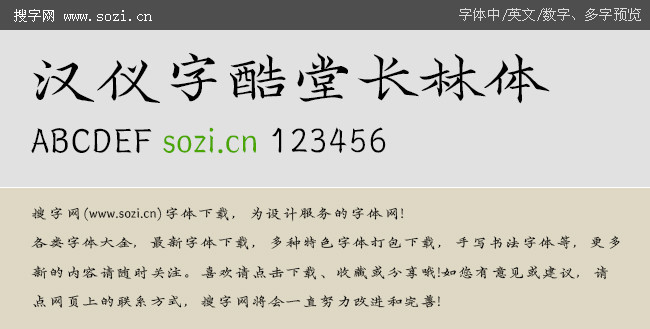
漢儀字酷堂長(zhǎng)林體
搜字網(wǎng)給大家提供一款漢儀字酷堂長(zhǎng)林體中文字體下載,漢儀字酷堂長(zhǎng)林體來源于清代名臣陳廷敬代表作品《午亭文編》,由林佶手書上版,結(jié)構(gòu)扁長(zhǎng),豎排效果佳,筆畫古雅圓潤(rùn)又富寫刻意味,生動(dòng)而有情致,適合應(yīng)用于書籍設(shè)計(jì)、平面海報(bào)設(shè)計(jì)、包裝設(shè)計(jì)等廣告應(yīng)用。(本字體為個(gè)人非商用版,如需要商用請(qǐng)聯(lián)系漢儀公司購買版權(quán))